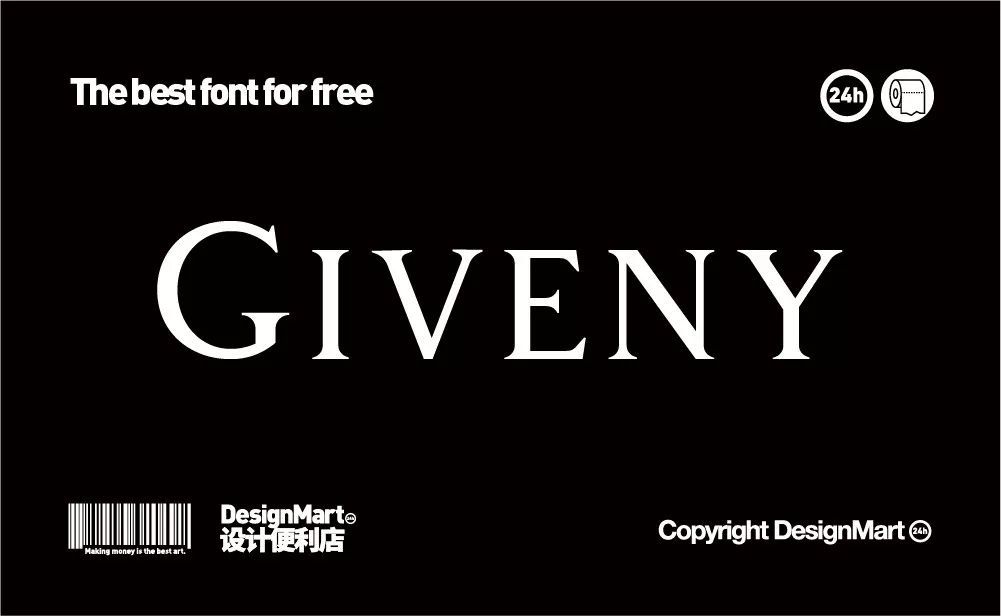
这款优雅的免费字体可以给设计带来极强的精致感。并且适用范围相当广泛,由Craft Supply Co.设计完成。提供多种语言字符,以及一系列标点符号。
字重:Regular、Italic
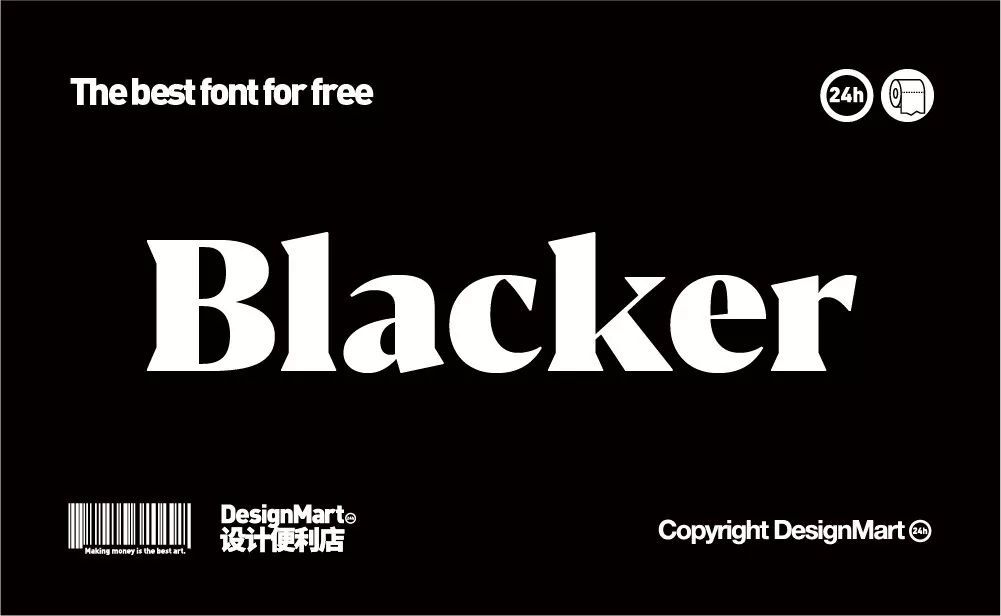
Blacker并不是一款传统的衬线字体,从经典设计中汲取灵感调整而来,设计师认为它是一种当代邪恶衬线体,具有高度的识别度、年代感的比例和尖锐的楔形衬线,字重非常全面,不过只有其中两款是完全免费的。
字重:Light、Medium Italic
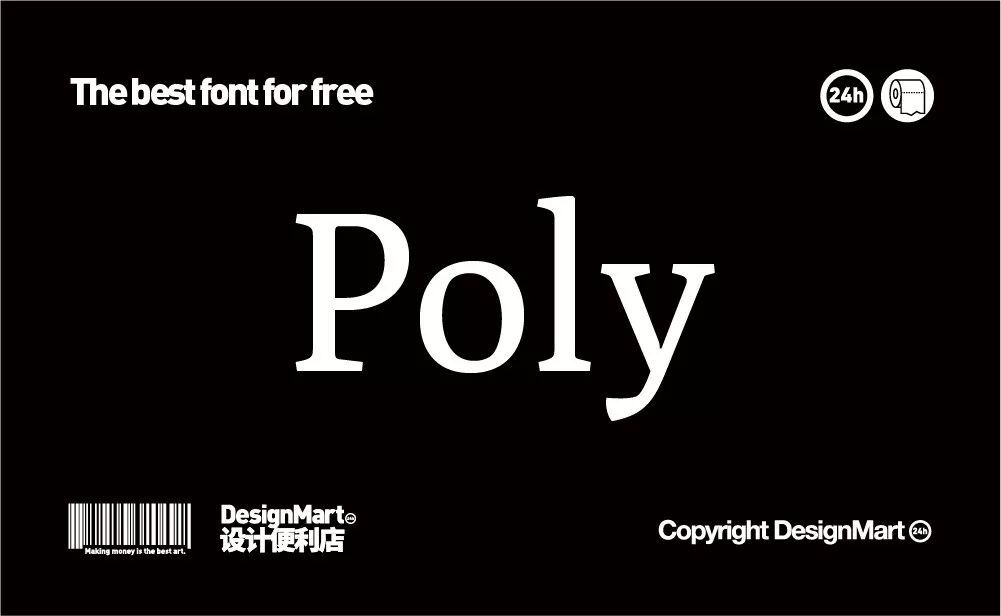
Poly是一款适用于Web中的衬线字体,即使在较小分辨率下也有非常优秀的易读性,它利用短的升部和非常高的X基线高度来确保字体识别的清晰度。
字重:Regular、Italic
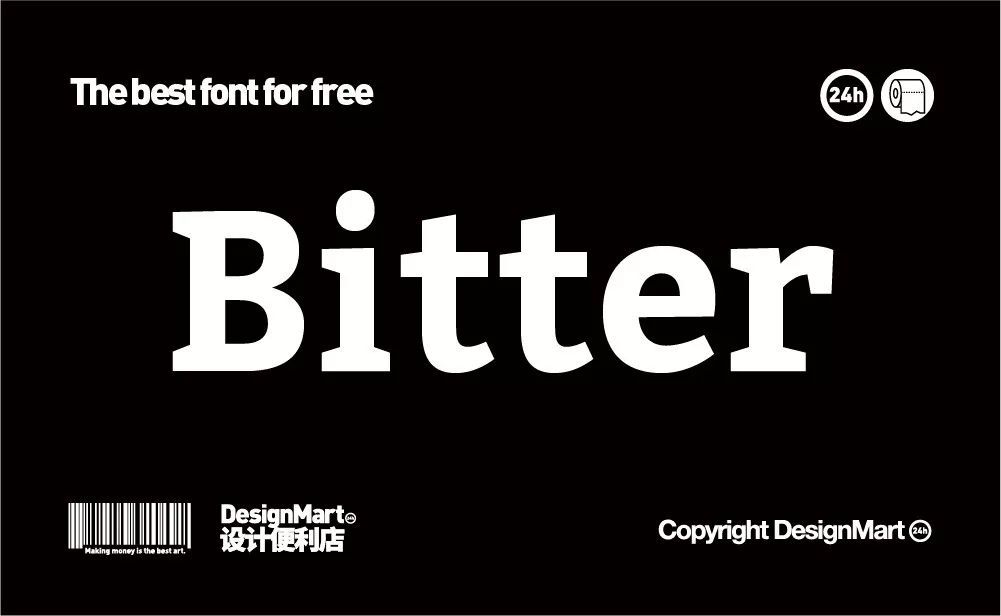
同样是一款能够在屏幕中表现优秀的衬线字体,它结合了常规的X基线高度且在粗细结构对比中使用了最小的变化。
字重:Regular、Bold
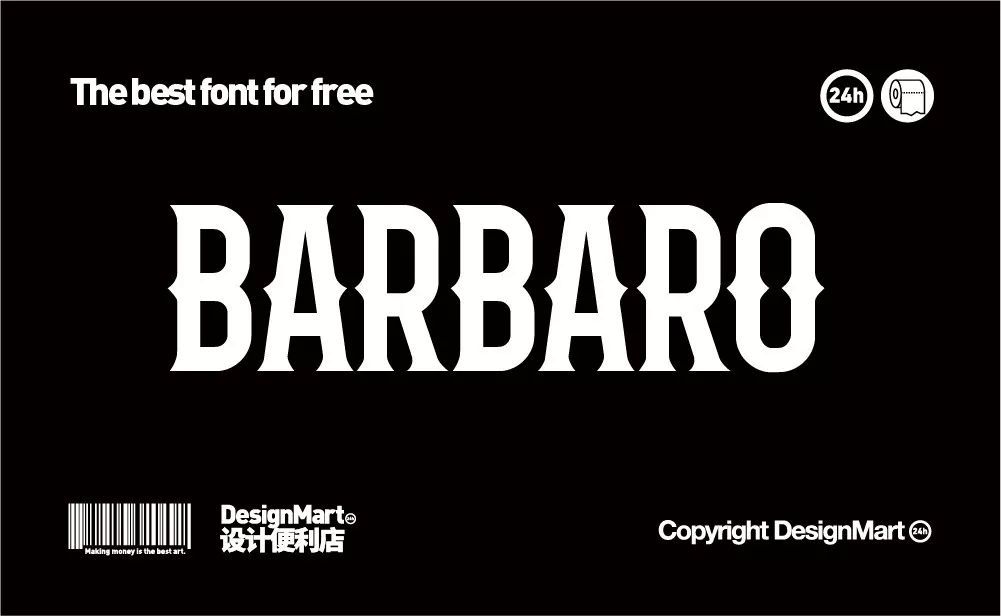
BarBaro包含了两个不同的字体风格,看起来哥特的风格让它能很好的运用在复古风格强烈的海报或是品牌设计中。
字重:Punta、Boman
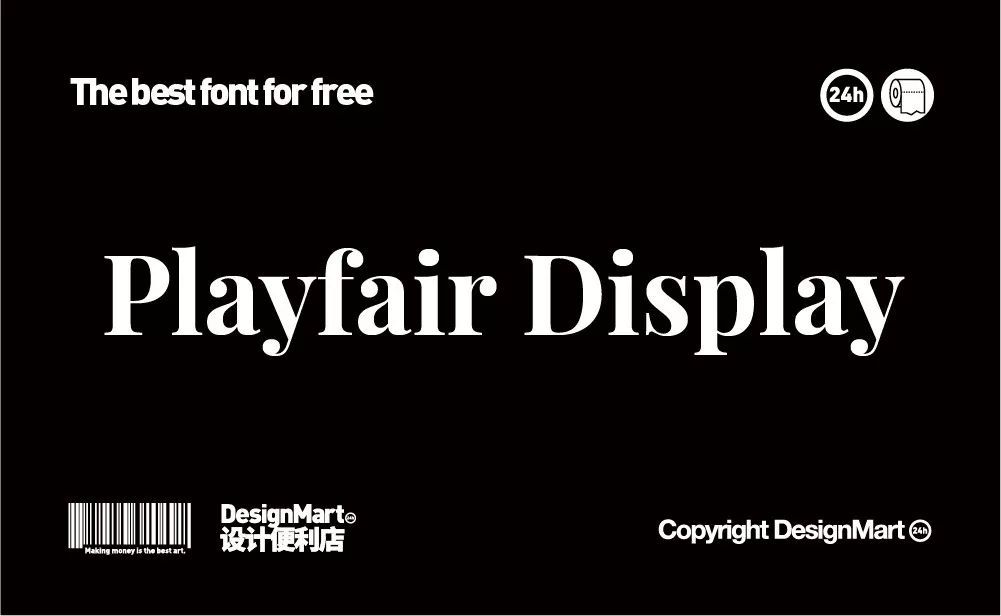
这是一款完全免费的开源字体,包含众多字重和格式,可以完美兼容不同操作系统,Playfair的灵感来自于18世纪晚期的欧洲艺术启蒙运动。
字重:Regular、Bold、Black
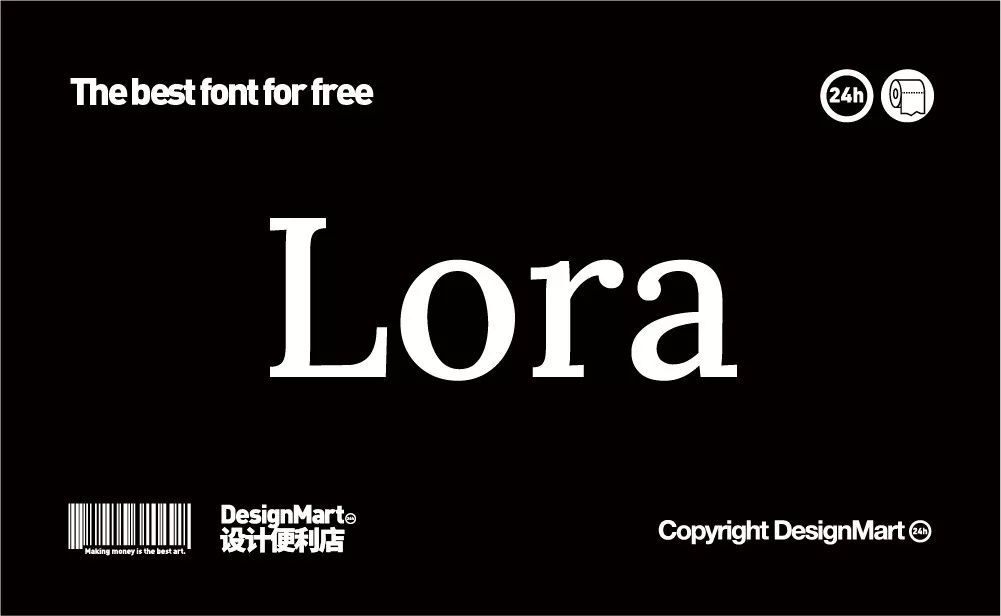
Lora是一款源于书法体的免费字体,最初由Cyreal设计,曲线部分和衬线部分的鲜明对比,赋予了这款字体均衡的现代感,尽管Lora在技术上已经经过优化,可用于网络呈现,但是它依然更适用于印刷项目。
字重:Regular、Medium、Bold
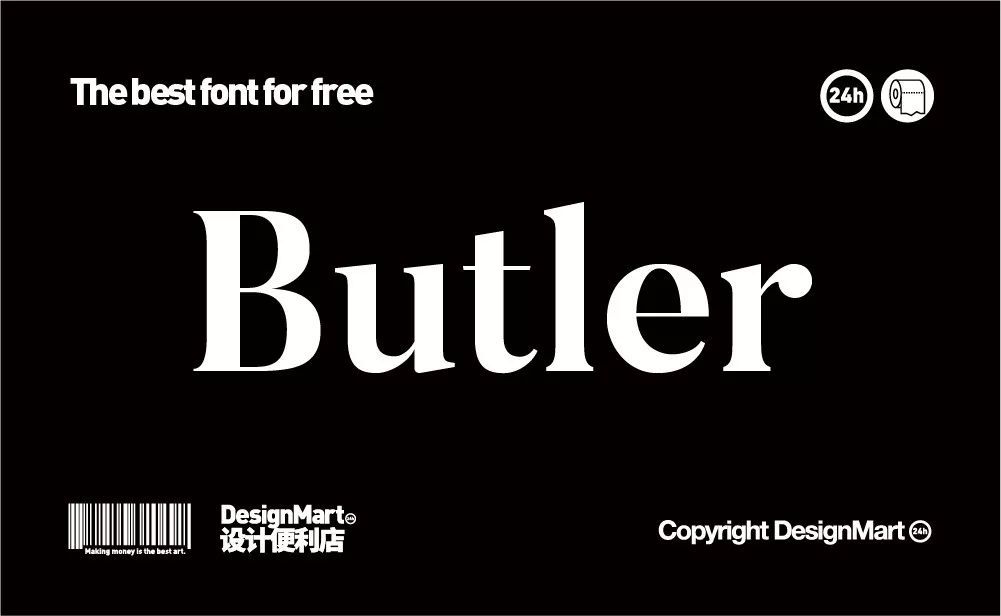
这款字体受到Dala Floda和BodoniPoly的影响,在经典的衬线体基础上,带来了一些现代主义,这款字体字重非常全面,且支持多种语言,标点符号和额外字形。
字重:全7种字重
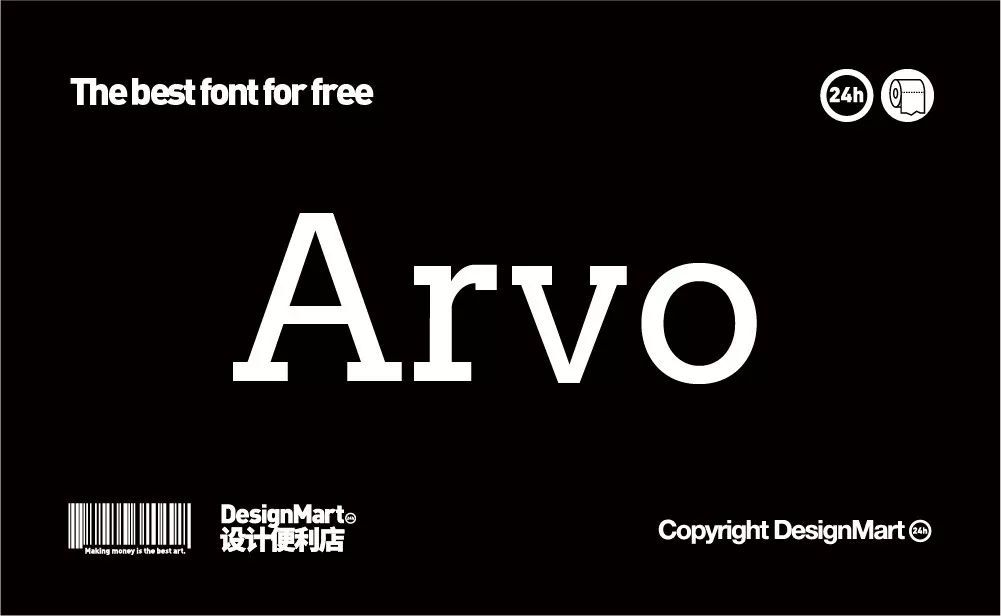
Arvo是一种几何平板衬线字体,适用于屏幕和打印用途,它专门为易读性而设计,作为免费开源字体在Google Font上发布,与Google中许多平板衬线不同,Arvo包含更多字重。
字重:Regular、Bold
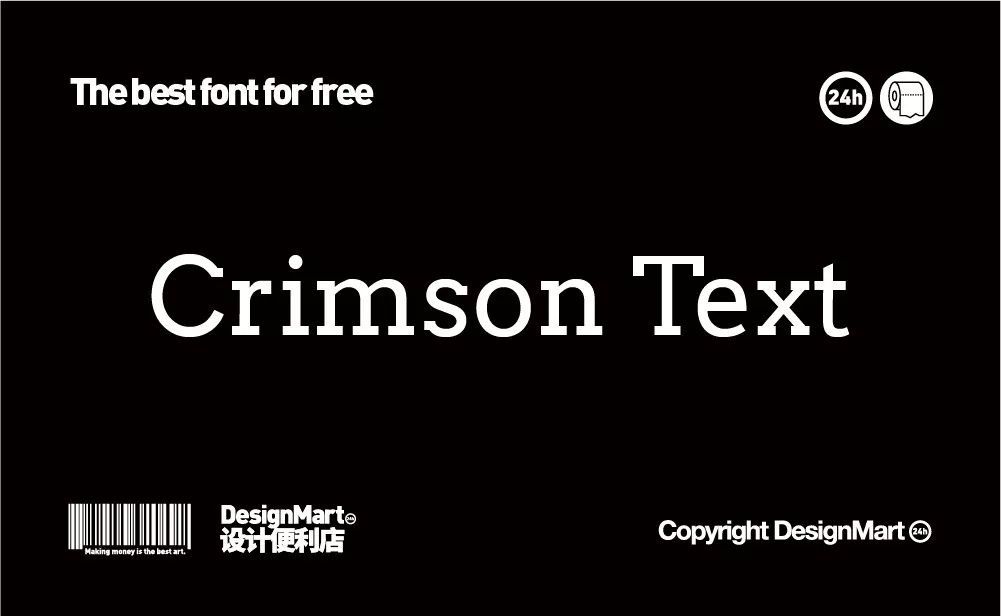
这是一款专门为图书制作而设计的免费字体系列,灵感来自于古老的Garamond式书籍字体,它具有非常富有表现力的斜体,与Futura或Avenir搭配都非常好用。
字重:Regular、Bold、SemiBlod
Aleo具有半圆形细节和光滑的结构,给人一种个性感,同时保持良好的易读性。这个免费的字体系列包括六种风格:三种重量(浅色,常规和粗体),以及相应斜体。
字重:light、Regular、Bold
Brela是一款非常人性化的衬线字体。它具有宽大的x高度,即使在很小的尺寸下也非常清晰,但它同样也适用于夸张的大标题。这个免费的字体是由西班牙创意机构马卡尔斯卡工作室设计。
字重:Regular
这是一款针对正文文字(通常为16px)优化的Web字体,他通过更高的X高度和更低的对比度,使其能够很好的在屏幕上阅读,这个字体还有一个姐妹字体Libre Franklin,也是免费字体哦。
字重:Regular、Bold
Slabo是一系列不断增长的特定尺寸的网络字体, 到目前为止,Slabo 27px和Slabo 13px已经完成,可以精确调整以适应特定像素尺寸。其结构的块状感赋予衬线字体的现代感,非常适合在线设计。
字重:Regular13px
由独立字体设计厂牌TypeTogether创建,Bree Serif是付费字体系列Bree的免费衬线表兄弟。Bree Serif被描述为“友好的直立斜体”,十分现代化,在较大的尺寸使用时具有相当优秀的易读性。
字重:Regular、Bold
Merriweather是一款真正开源的免费衬线字体,在GitHub上有自己的项目。它由Sorkin Type设计,十分易于在屏幕上阅读,并且在在Google Fonts中有非常高的人气!
字重:light、Regular、Bold、Black
又是一个开源字体系列,专为多种现代用途而设计,适用于标题,段落,印刷品和网络。这是该字体的第二个版本,有七种样式。没有斜体(创作者认为在现代不需要斜体),字体涵盖了大多数拉丁语和西里尔语。
字重:7种字重